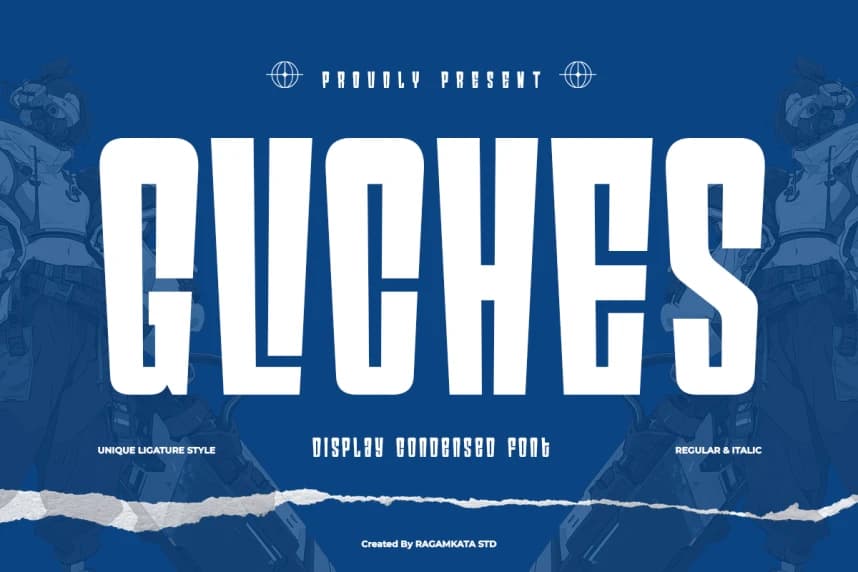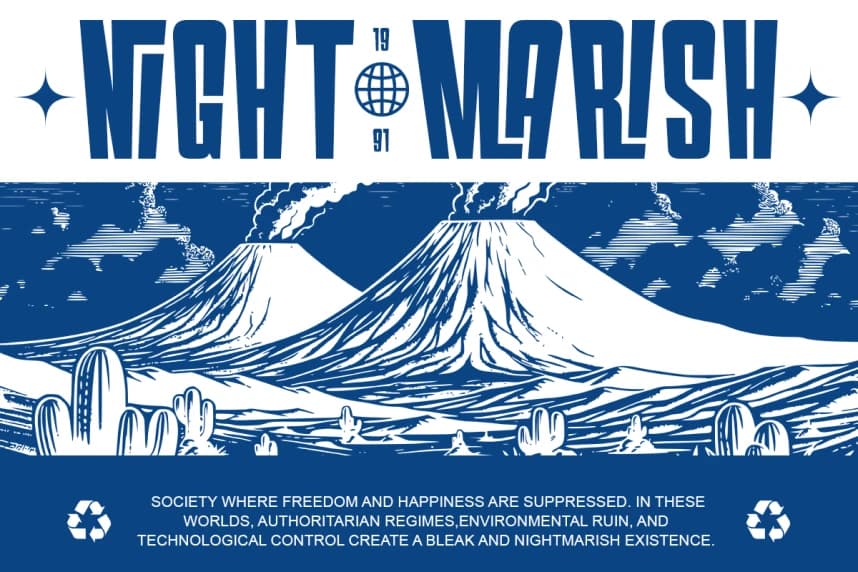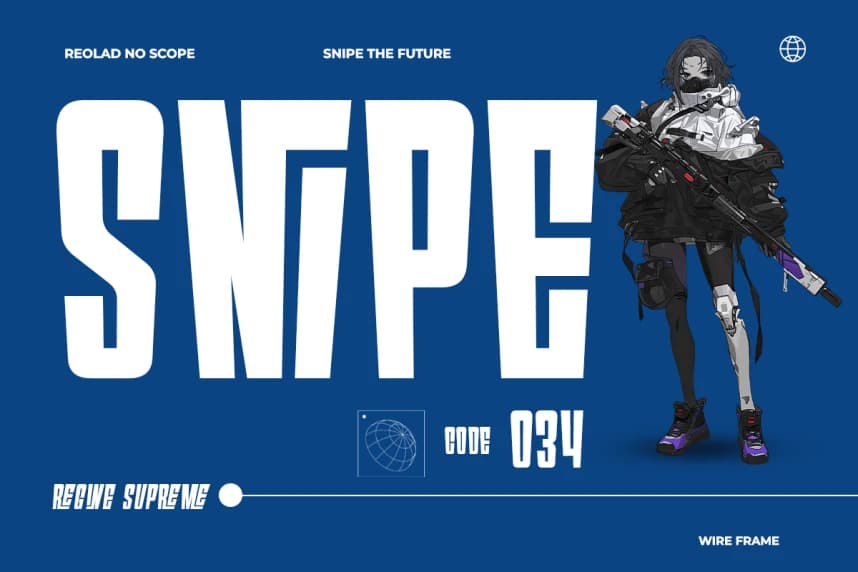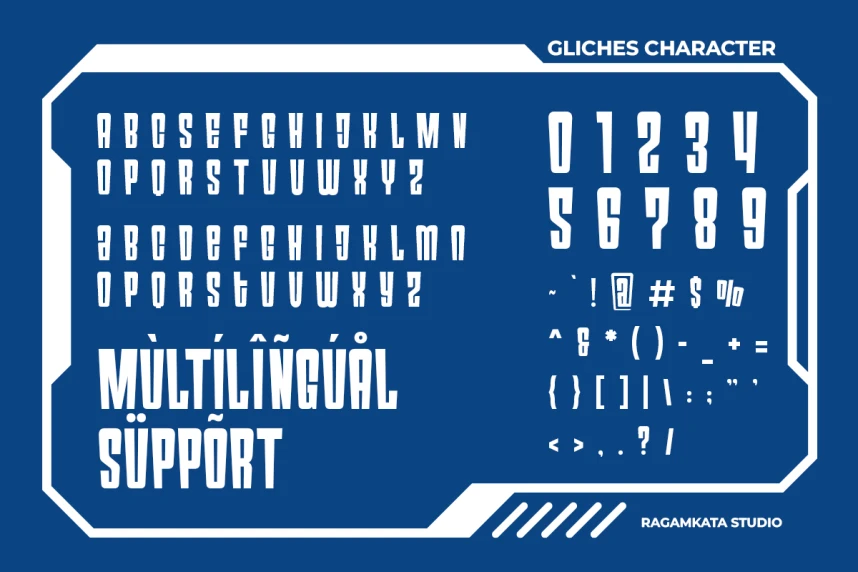
Gliches Font
Gliches Font, yüksek etkiye sahip görseller ve güçlü tipografik varlık için tasarlanmış kalın sıkıştırılmış bir gösterim yazı tipidir. Modern oyun estetiğinden ve kentsel afiş kültüründen ilham alan bu yazı tipi, kompakt yapı ile güçlü okunabilirlik arasında çarpıcı bir denge sunar.
Gliches Font, yüksek etkiye sahip görseller ve güçlü tipografik varlık için tasarlanmış kalın sıkıştırılmış bir gösteri yazı tipidir. Modern oyun estetiği ve kentsel poster kültüründen ilham alan bu yazı tipi, kompakt yapı ile güçlü okunabilirlik arasında çarpıcı bir denge sunar.